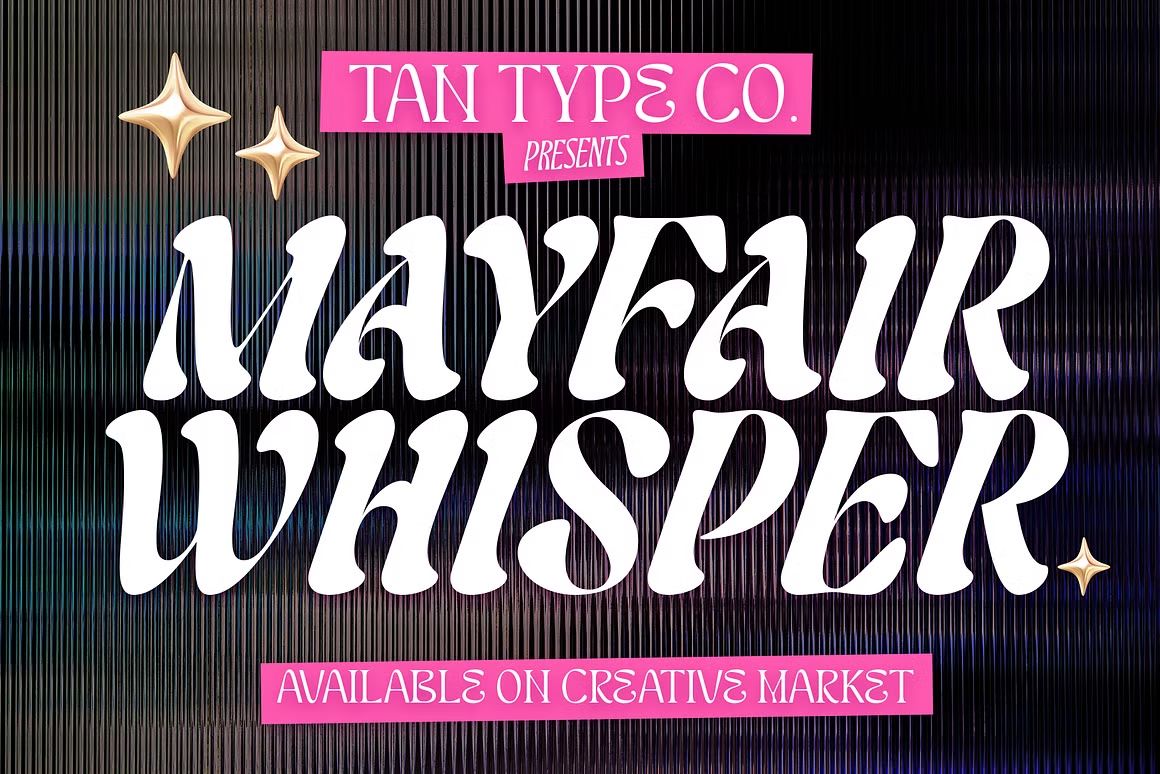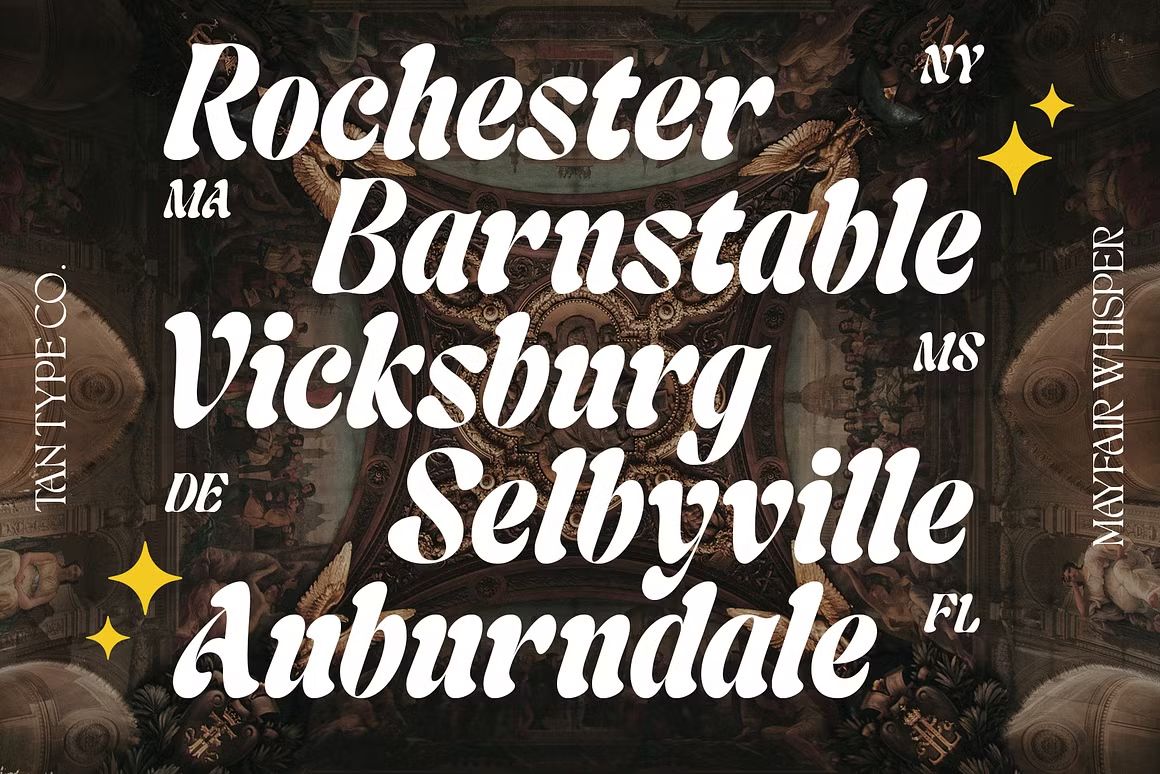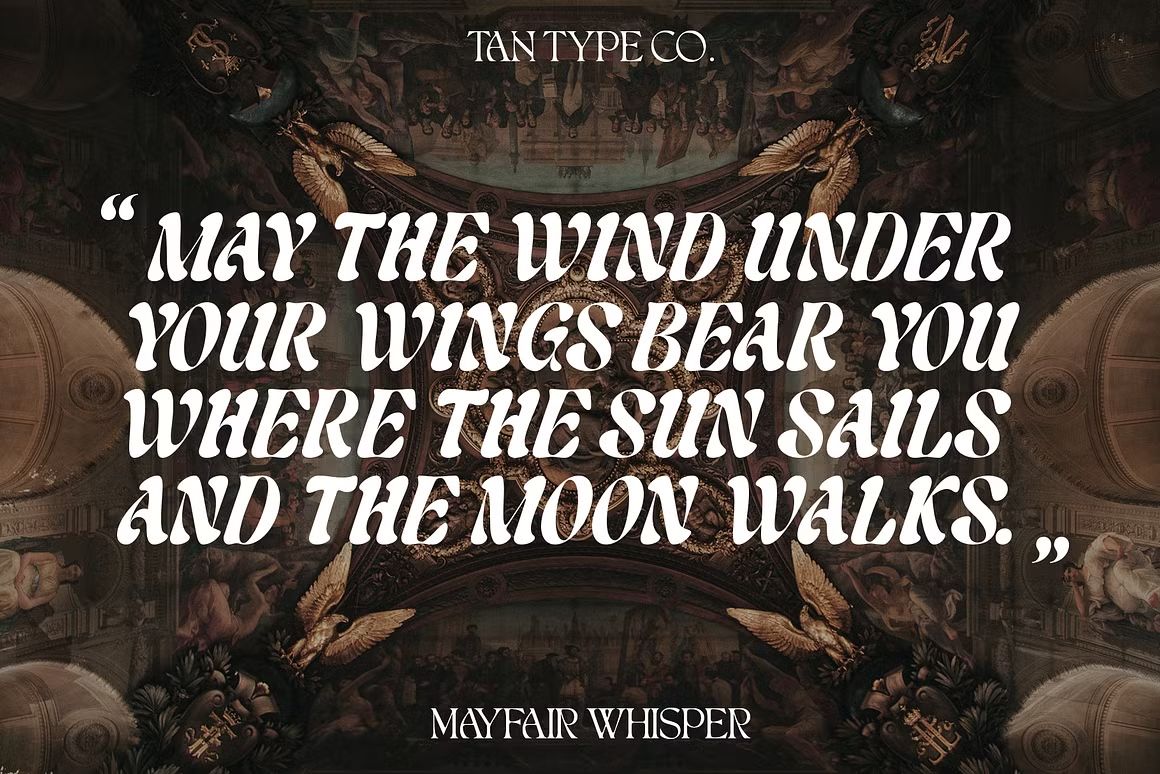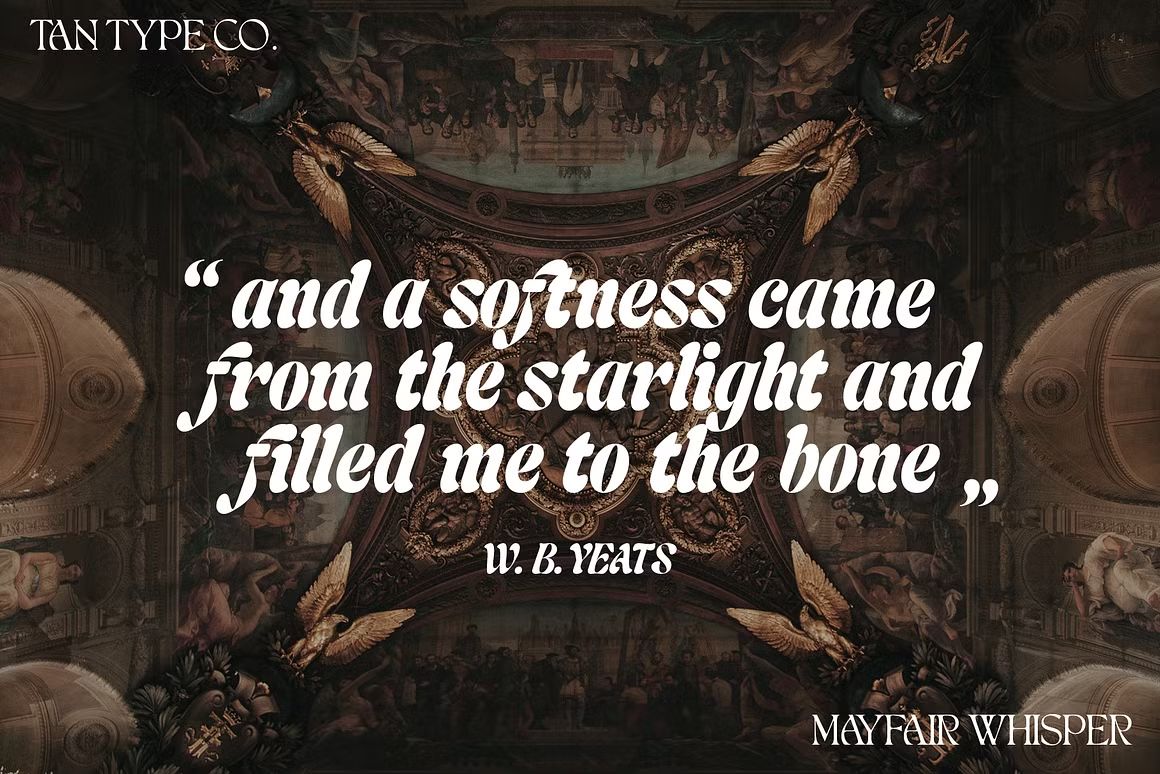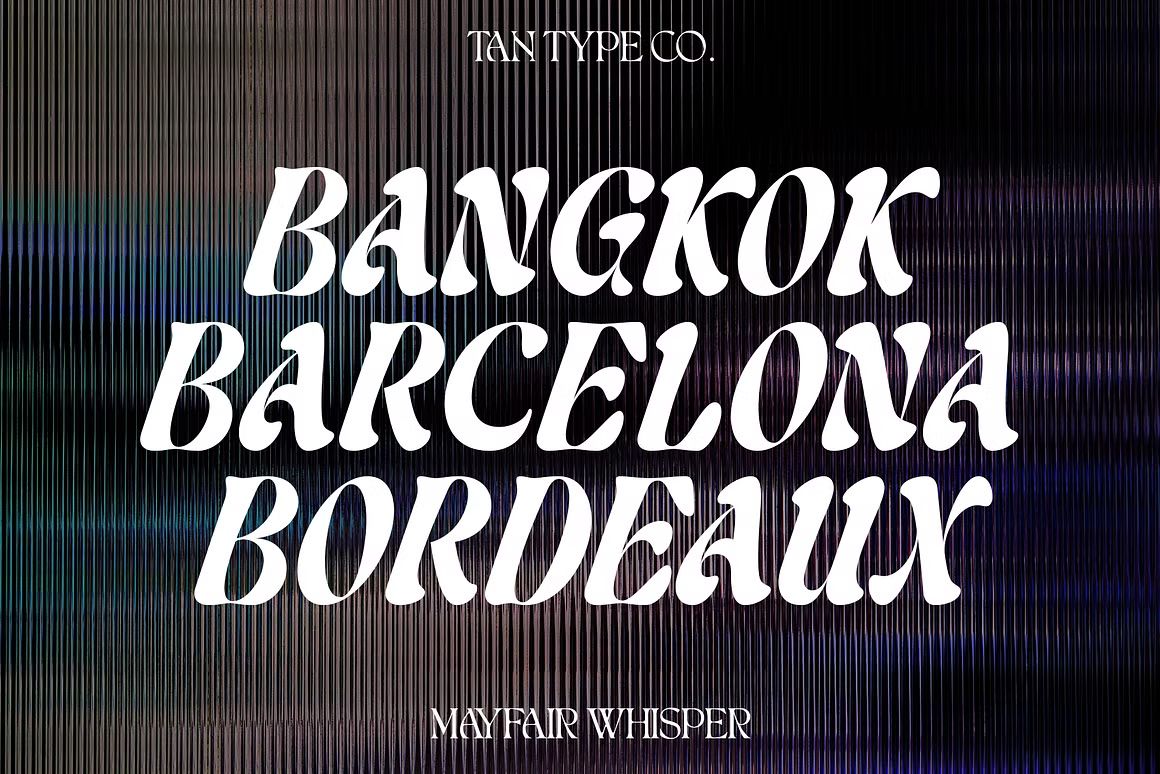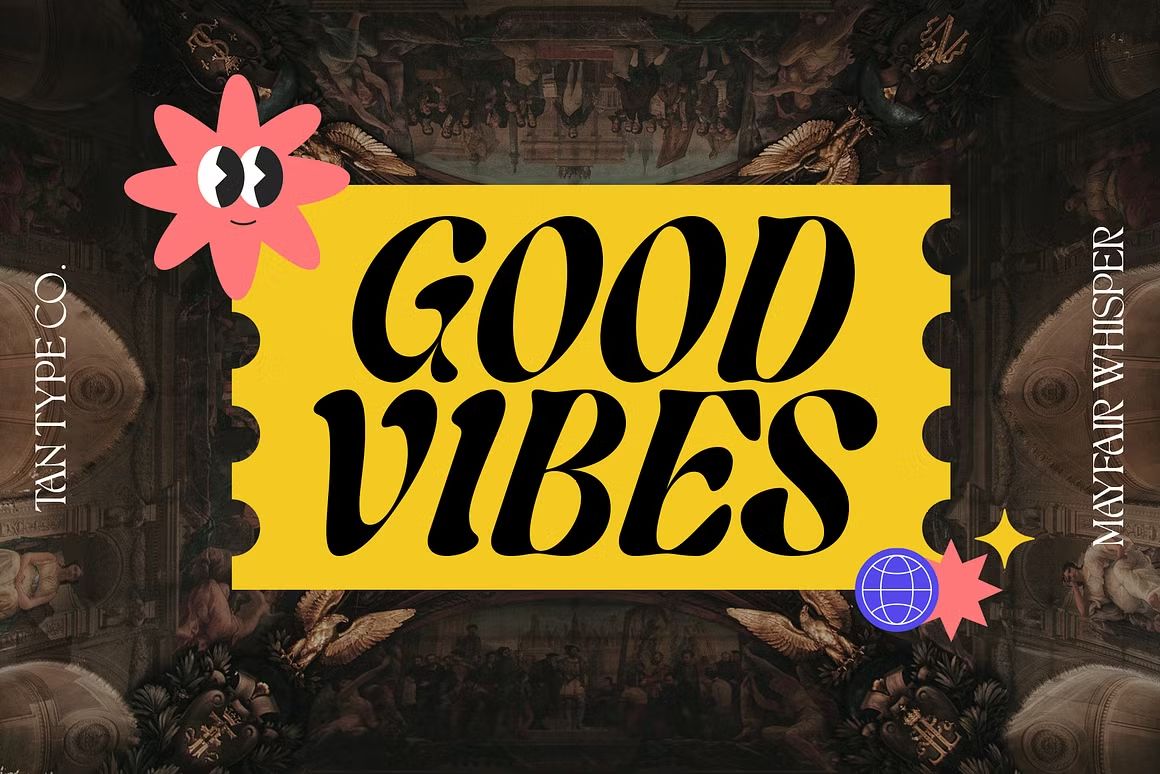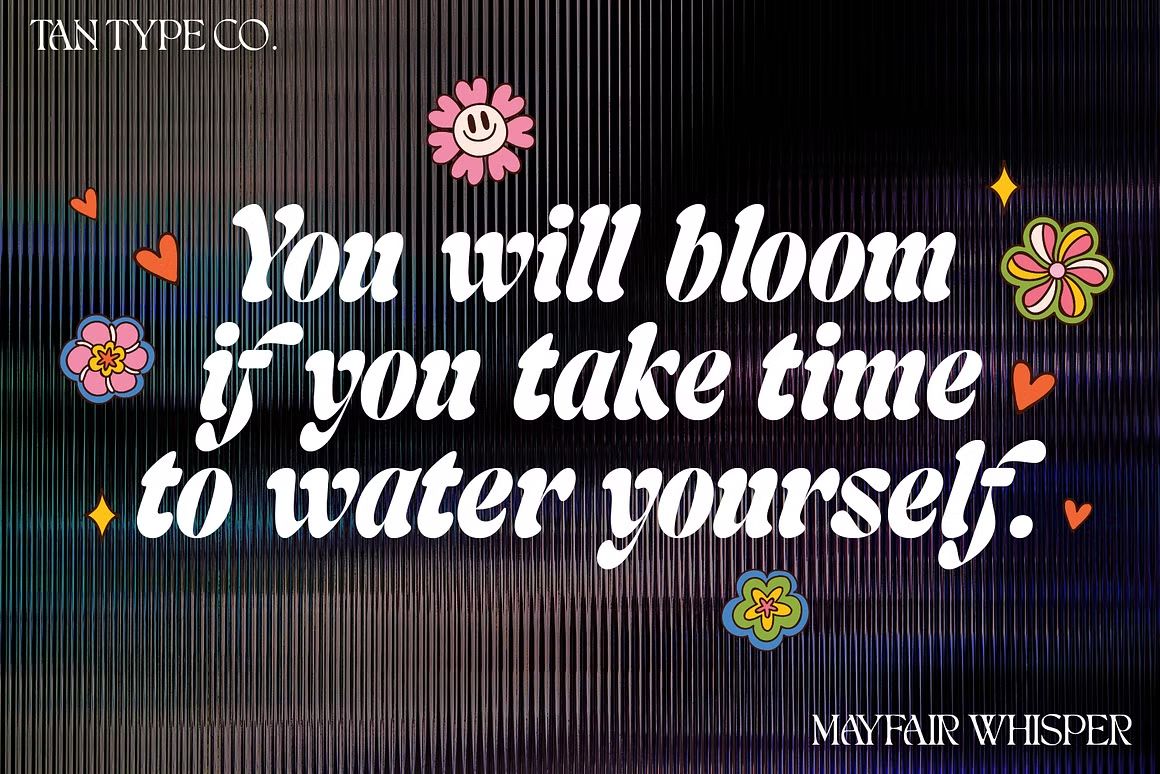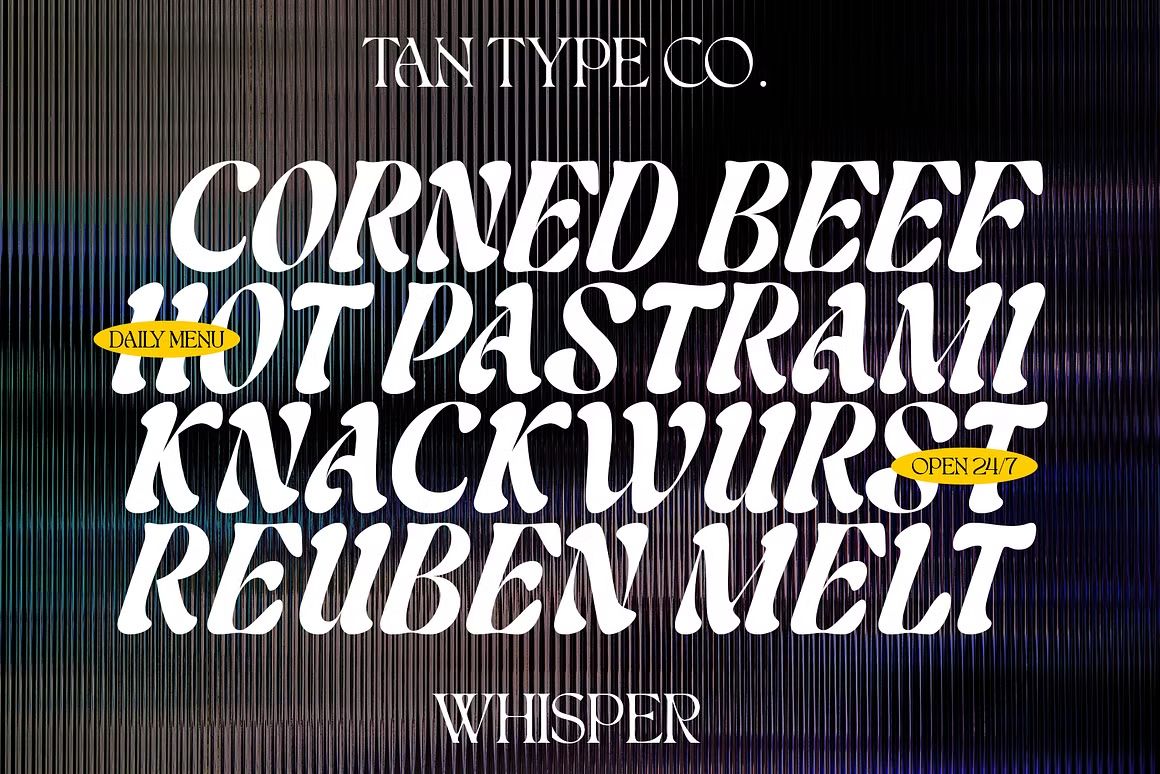
Mayfair Whisper – Script Font
Mayfair Whisper adalah font script elegan dan lembut, cocok untuk wedding, logo mewah, dan desain estetik. Format OTF/TTF/WOFF, siap digunakan.
Mayfair Whisper adalah font script bergaya anggun dan feminin dengan goresan halus serta alur tulisan tangan yang elegan. Cocok untuk desain bertema romantis dan mewah seperti undangan pernikahan, logo kecantikan, kemasan produk premium, kutipan estetik, dan konten media sosial. Font ini menghadirkan kesan lembut, stylish, dan profesional.
• Script font dengan alur elegan dan feminin
• Ideal untuk wedding, branding, dan desain premium
• Termasuk huruf besar, kecil, angka, simbol, dan ligatur